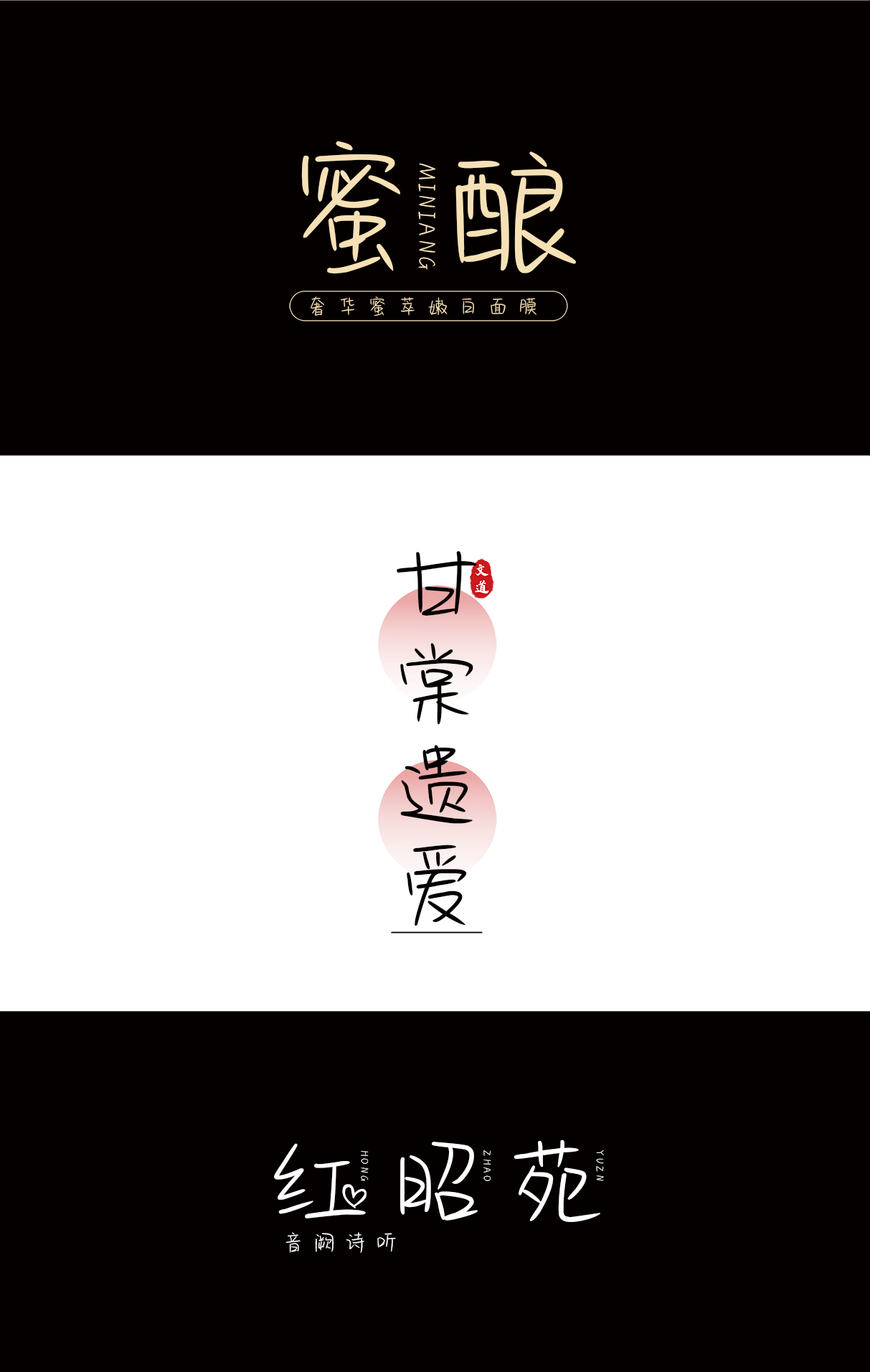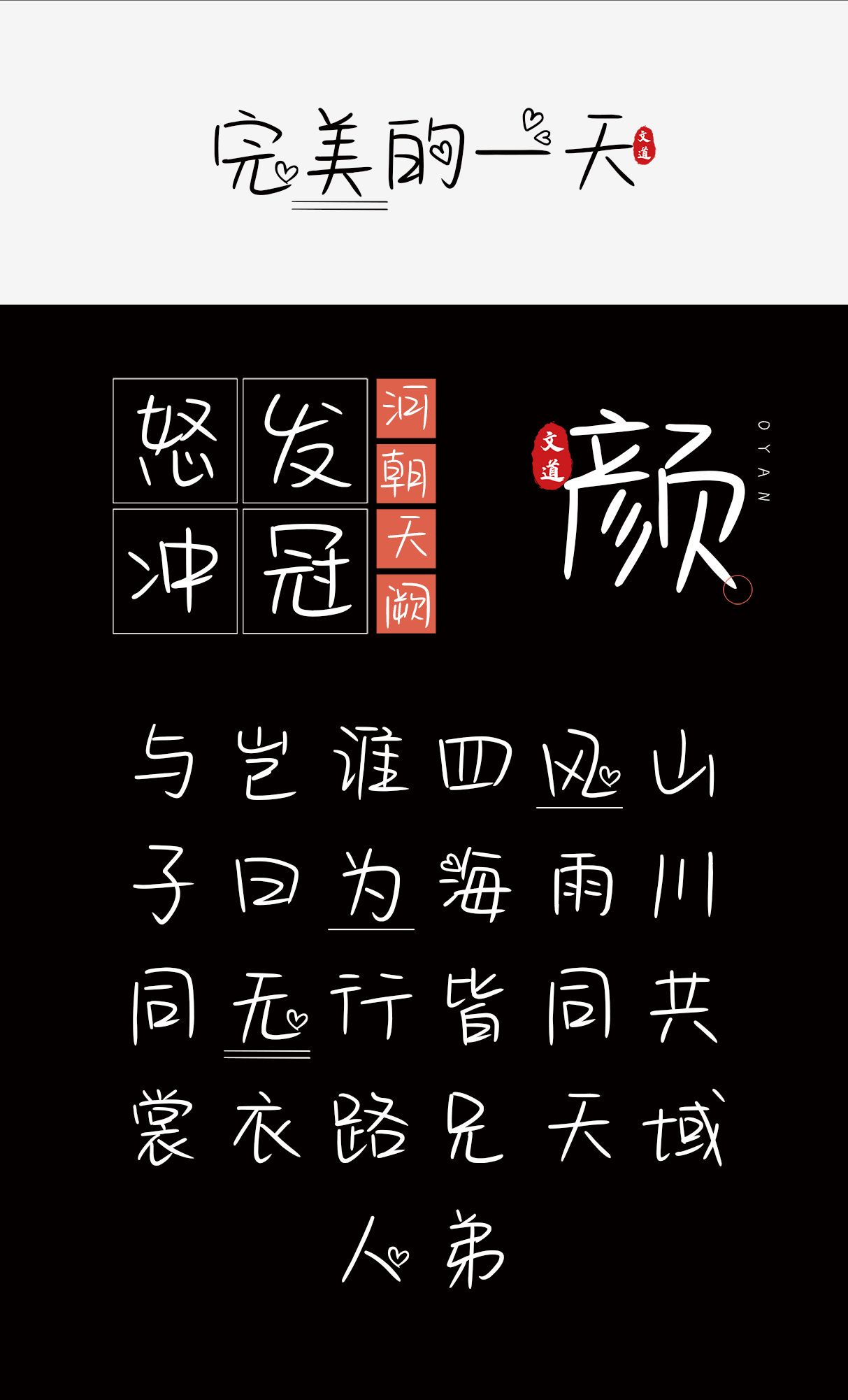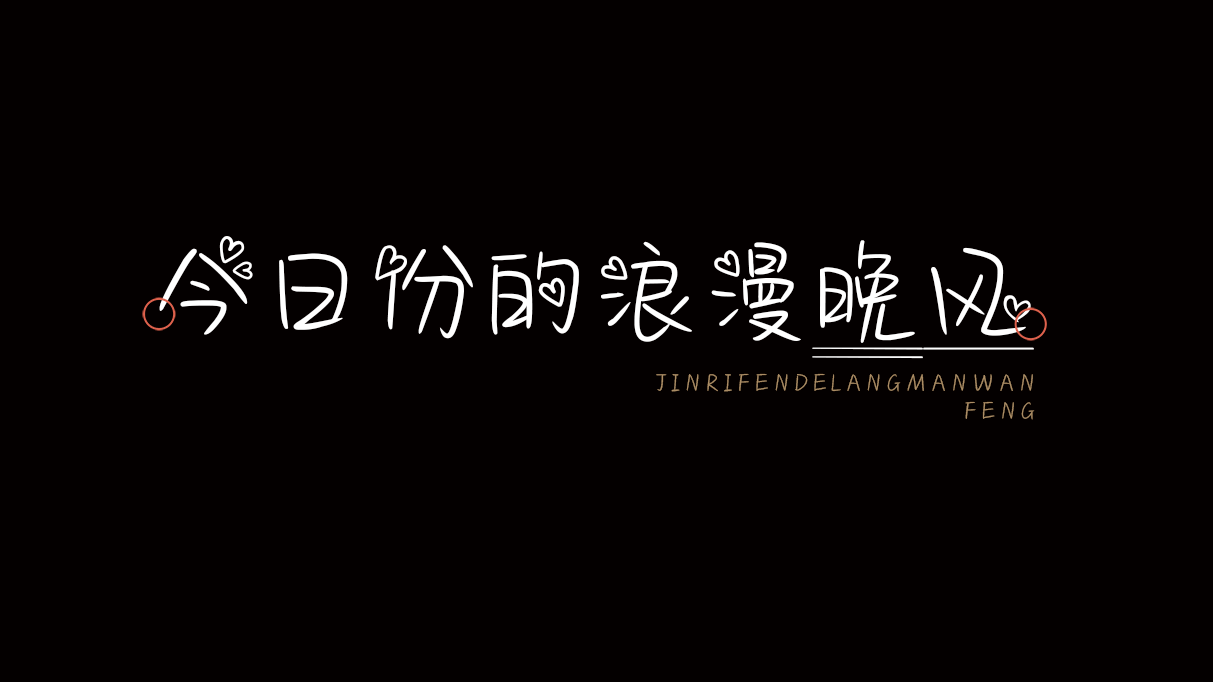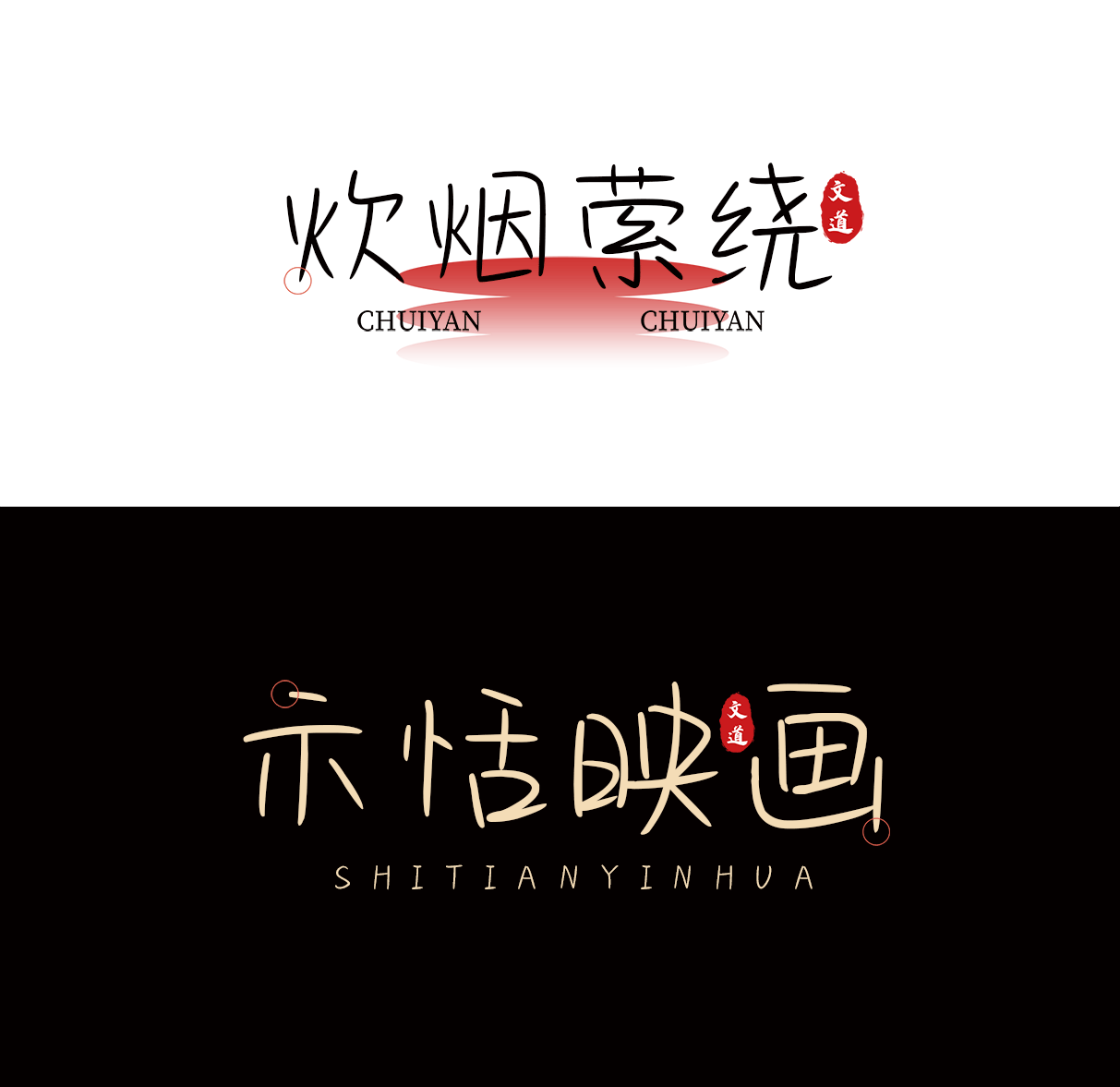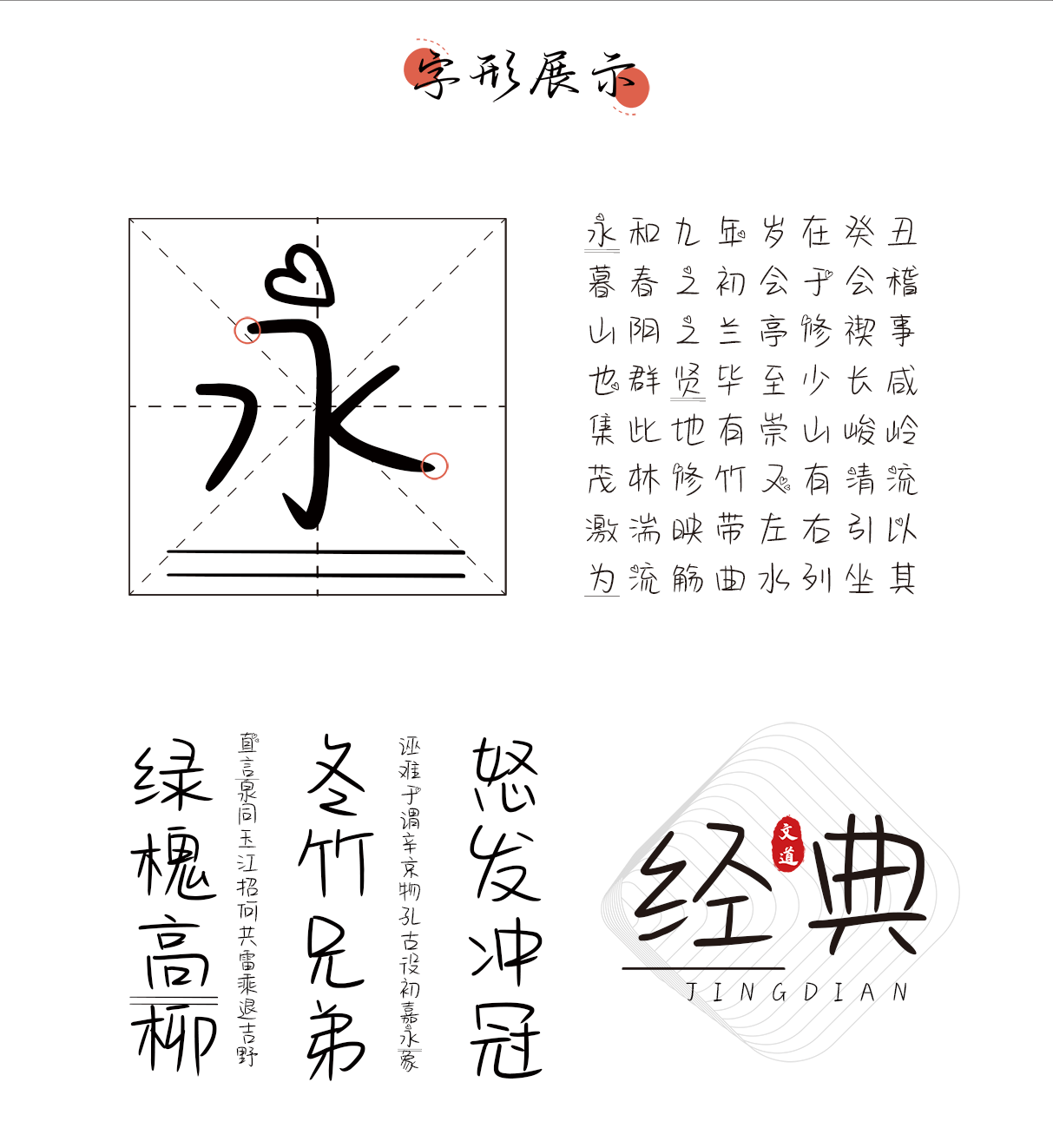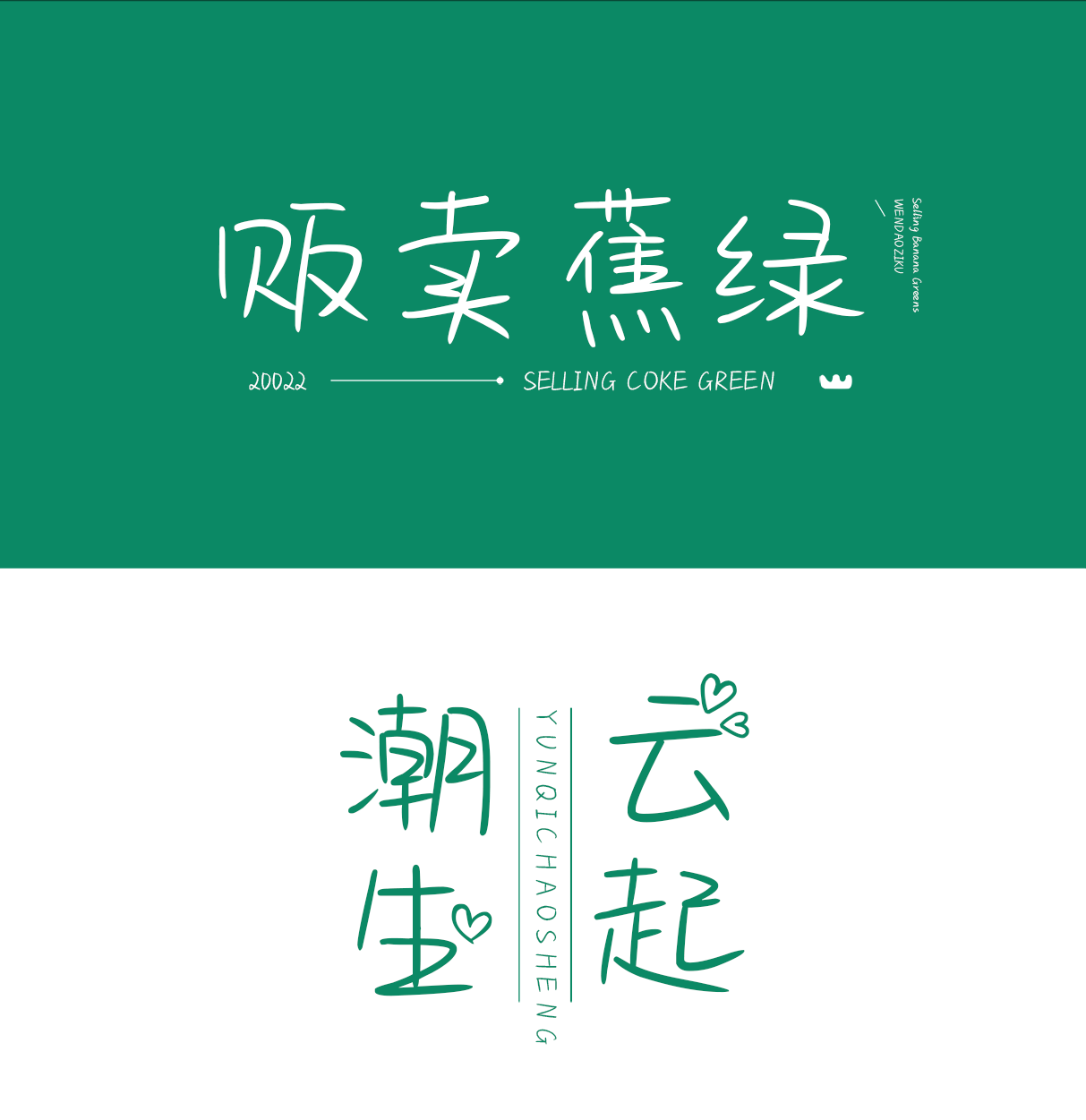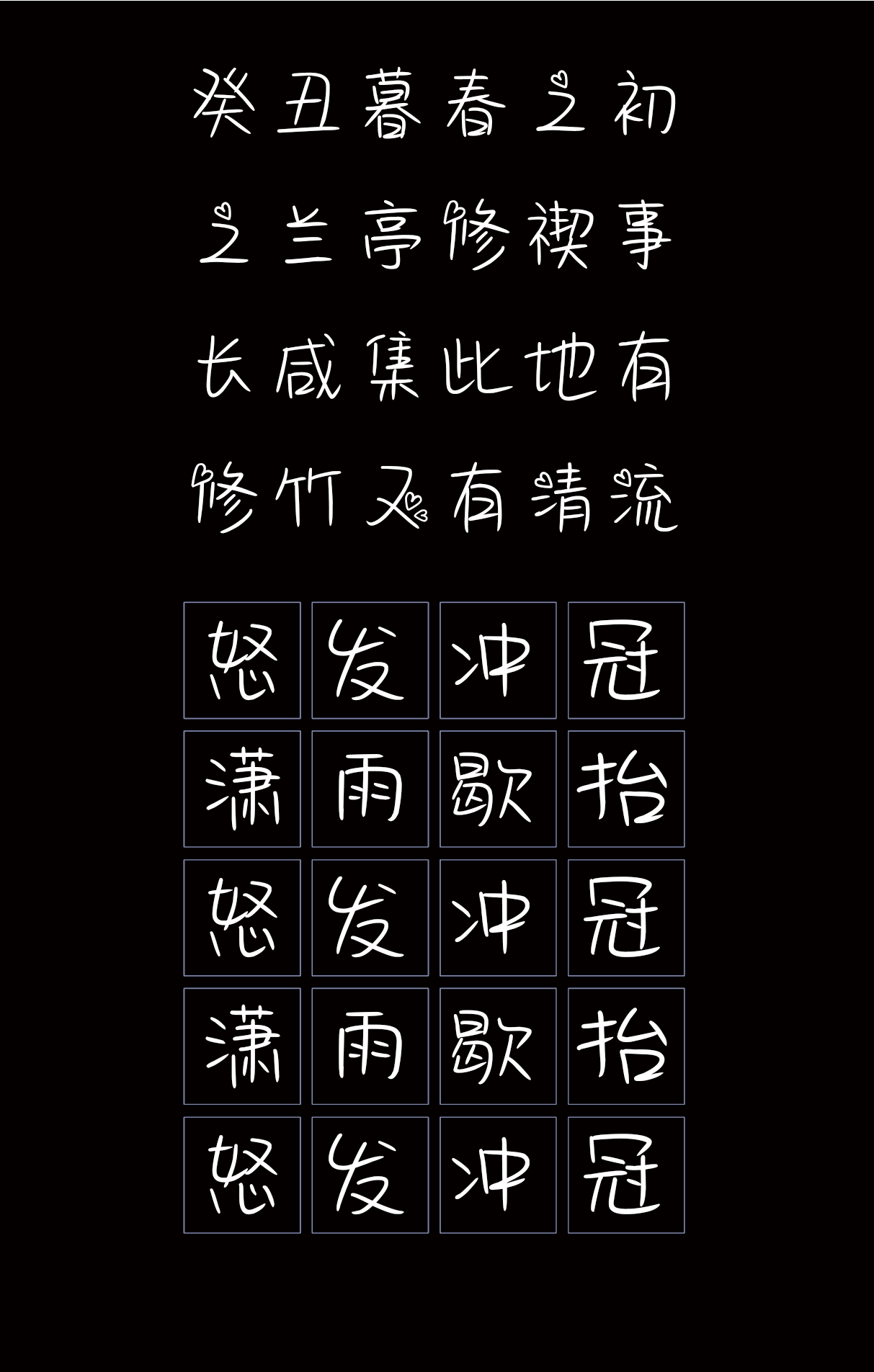
今日份的浪漫晚风
文亦有道,笔墨添香;墨韵飞扬,意蕴绵长。
字体名称: 今日份的浪漫晚风
简介: 【今日份的浪漫晚风】是一款可商用创意体,笔画之前留有一丝间隙的设计使得每个字体看起来不是个性,该字包含6763个中文、字母、符号和数字,可用于印刷媒介的各类标题,字体风格正好适用于屏幕显示、广告标语和产品类包装设计。